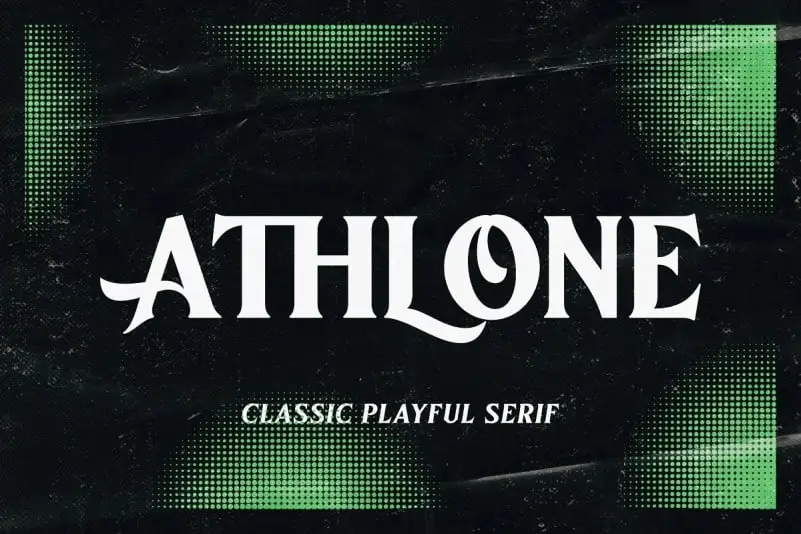
Athlone Serif Font – Download Grátis
A Athlone Serif Font é uma opção elegante para quem procura um tipo serif vintage que reflete a qualidade dos antigos estilos tipográficos. Confeccionada com grande cuidado nos detalhes, ela apresenta linhas claras e bordas afiadas, junto com curvas sedutoras. O design inclui uma versão arredondada que oferece mais flexibilidade para suas criações, permitindo-lhe experimentar diferentes texturas e estilos. Perfeita para aplicação em títulos e headlines, logotipos e identidades visuais, embalagens e rótulos, esta fonte representa uma maneira de incorporar elegância no seu design. Não importa o tipo de projeto que você está criando, a Athlone Serif Font oferece um encaixe perfeito para torná-lo único e profissional. Experimente agora e descubra como ela pode adicionar um toque especial ao seu trabalho visual.